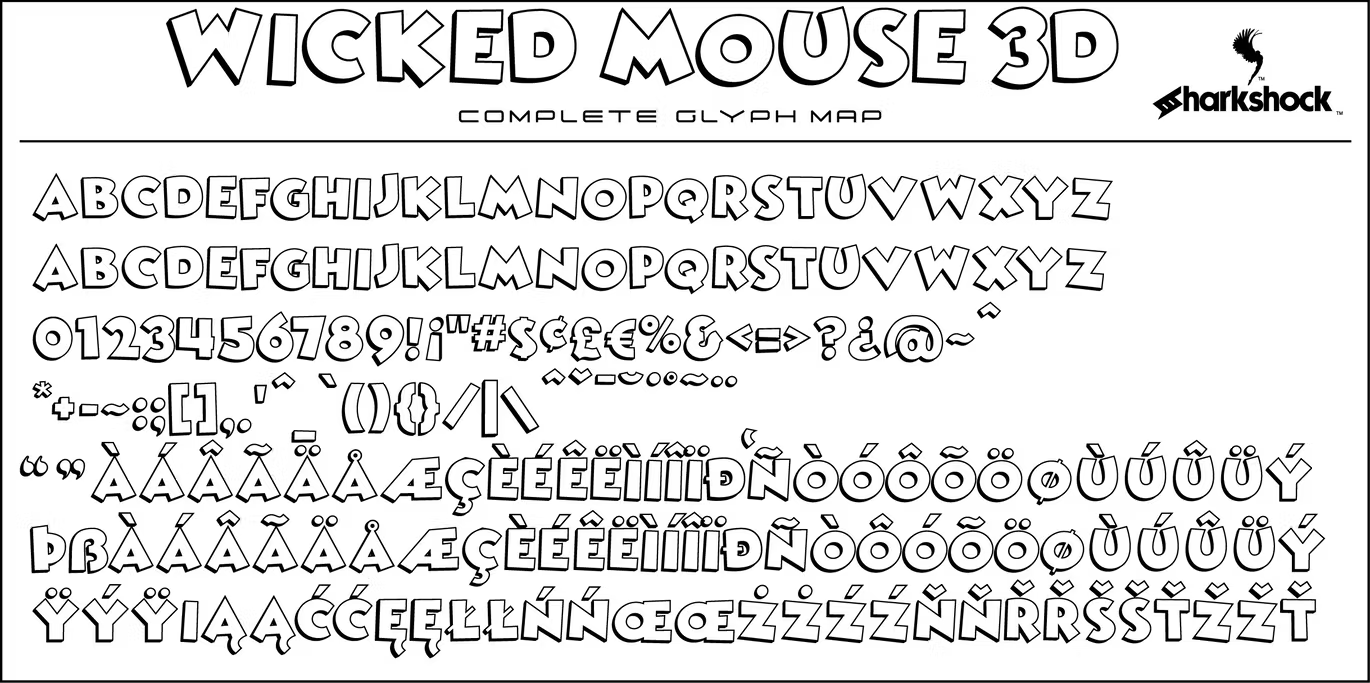
Wicked Mouse Font
Description de Wicked Mouse Font
Gardez vos chapeaux les amis ! Wicked Mouse est une police d’affichage ludique en majuscules qui capture la magie des dessins animés d’une époque lointaine. Le latin de base, le latin étendu, la ponctuation, les accents européens et les signes diacritiques sont inclus. Les caractères minuscules diffèrent légèrement en termes de variation et de rotation dans la version standard, tandis qu’ils reflètent leurs homologues majuscules dans la version 3D. Vérifiez les cartes de glyphes incluses pour tous les personnages. (un léger chevauchement est à prévoir avec certains personnages) Utilisez Wicked Mouse pour un livre pour enfants, des pages Web ou un logo amusant. Libérez l’enfant qui sommeille en vous !